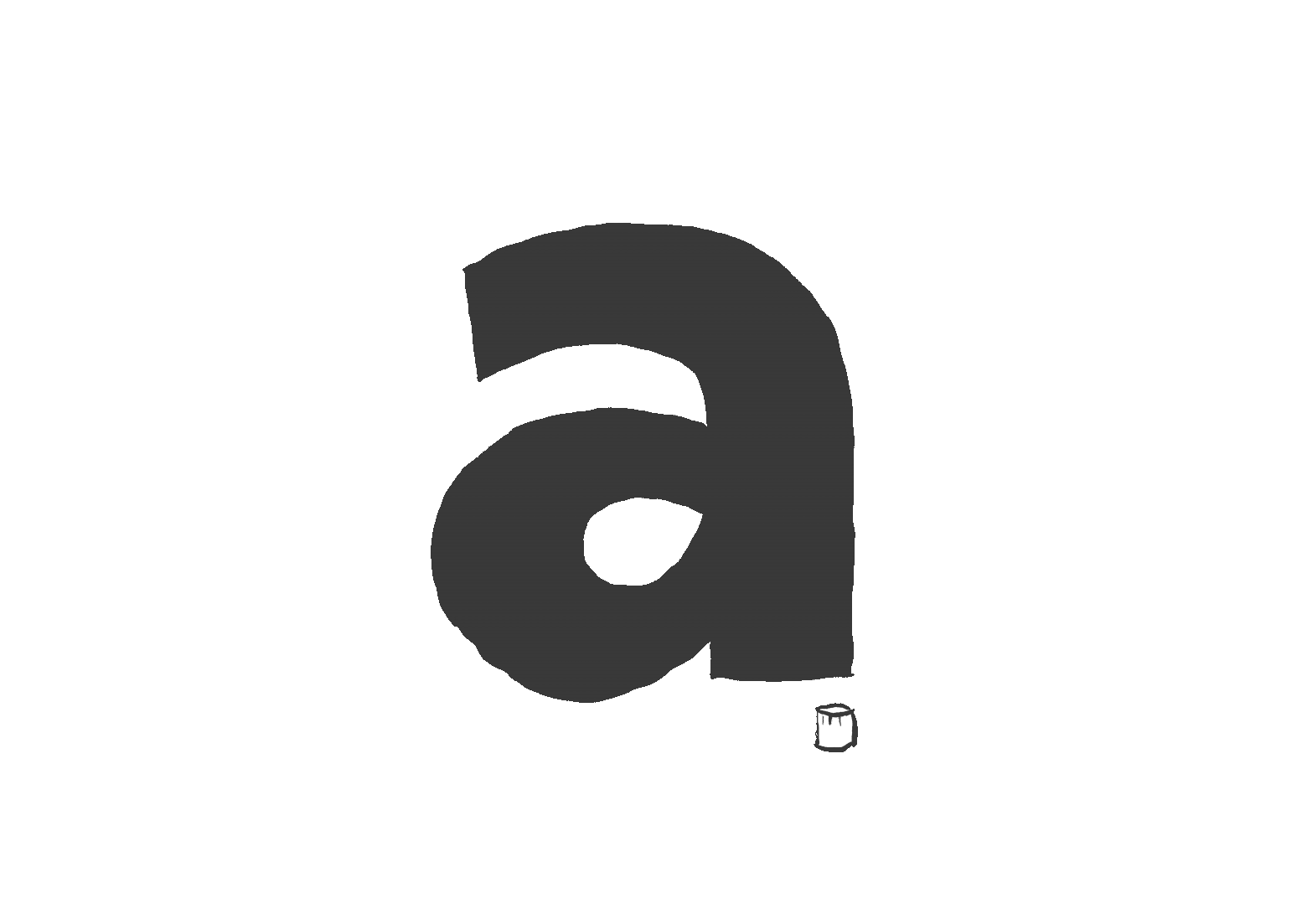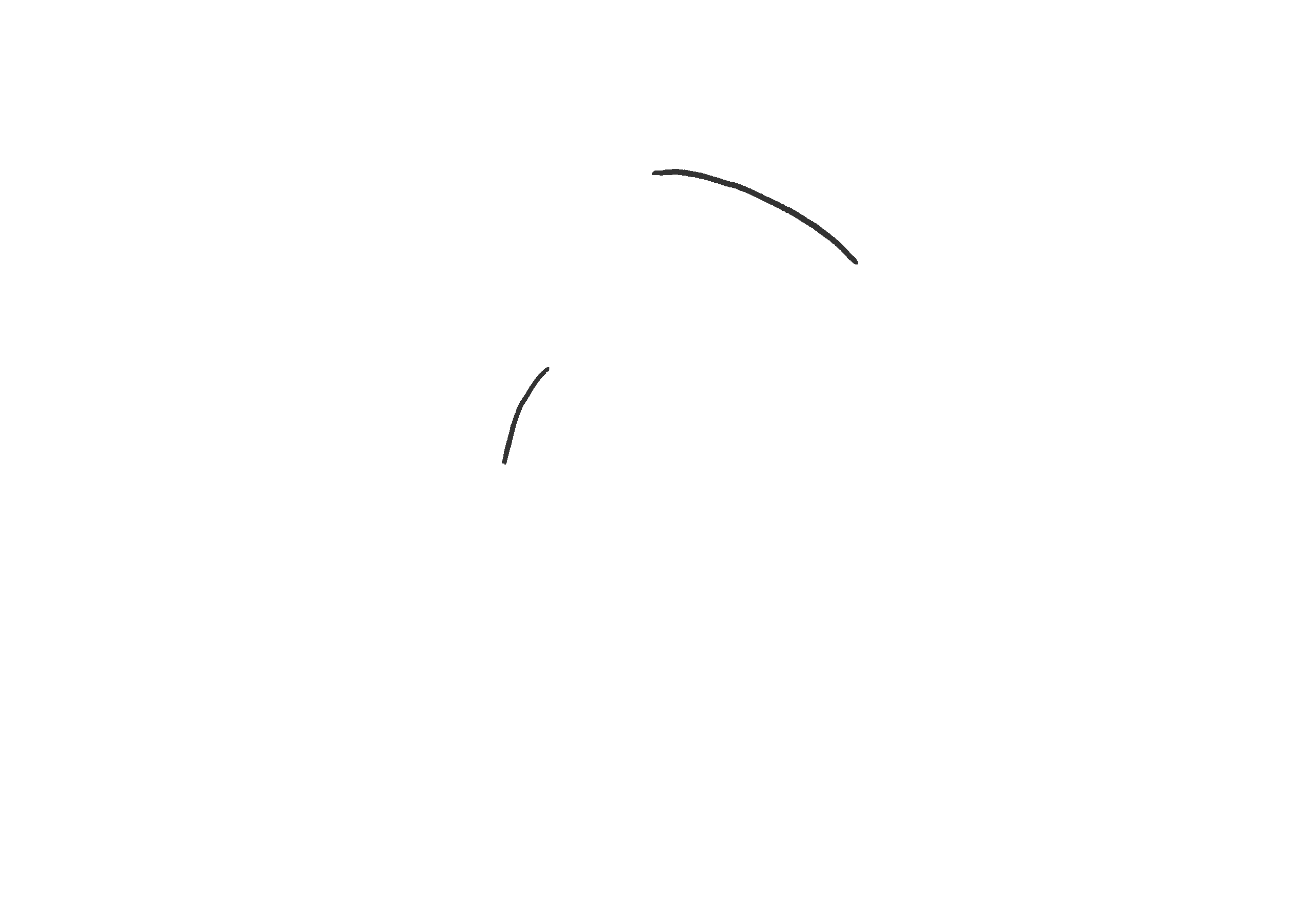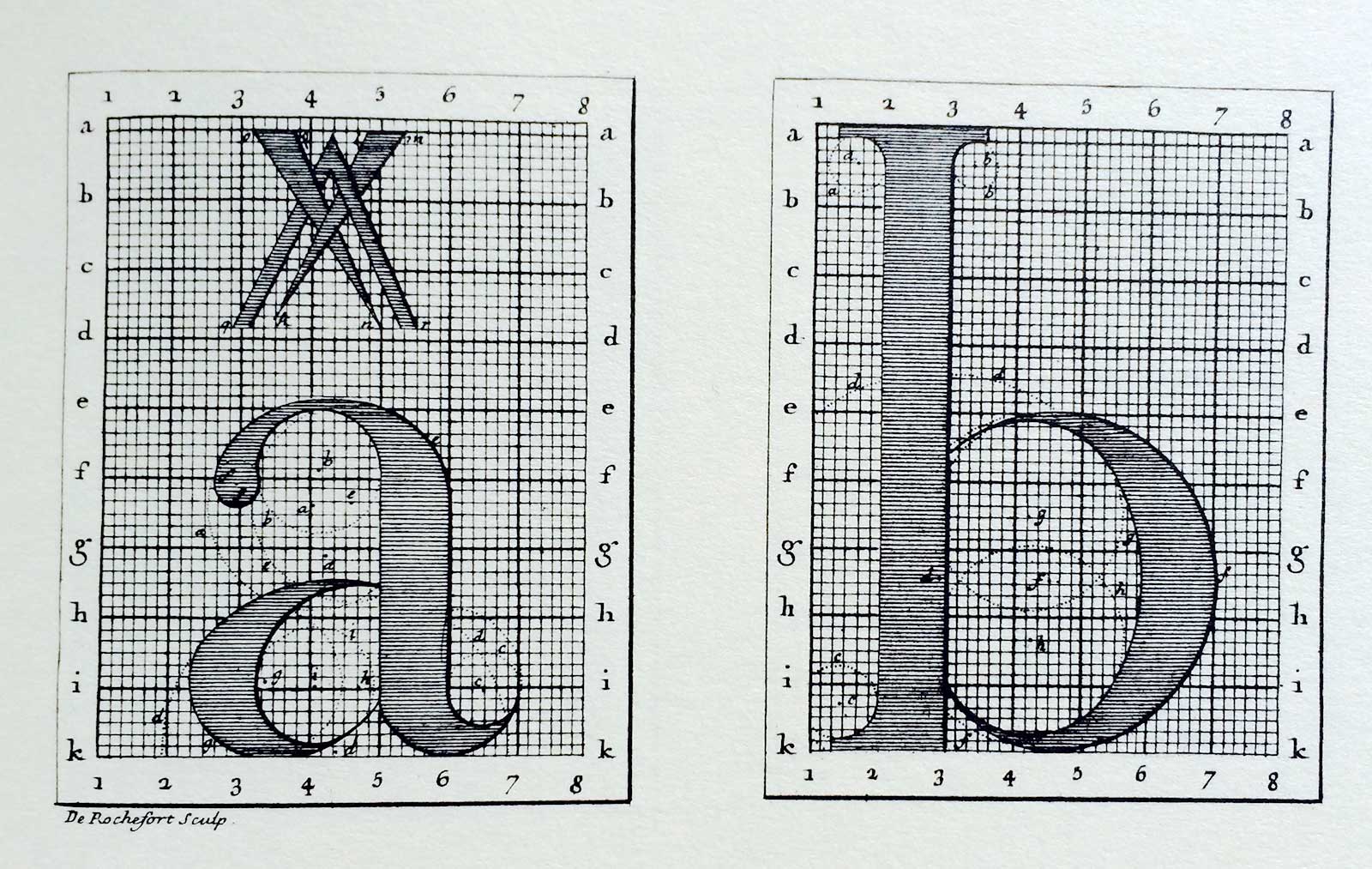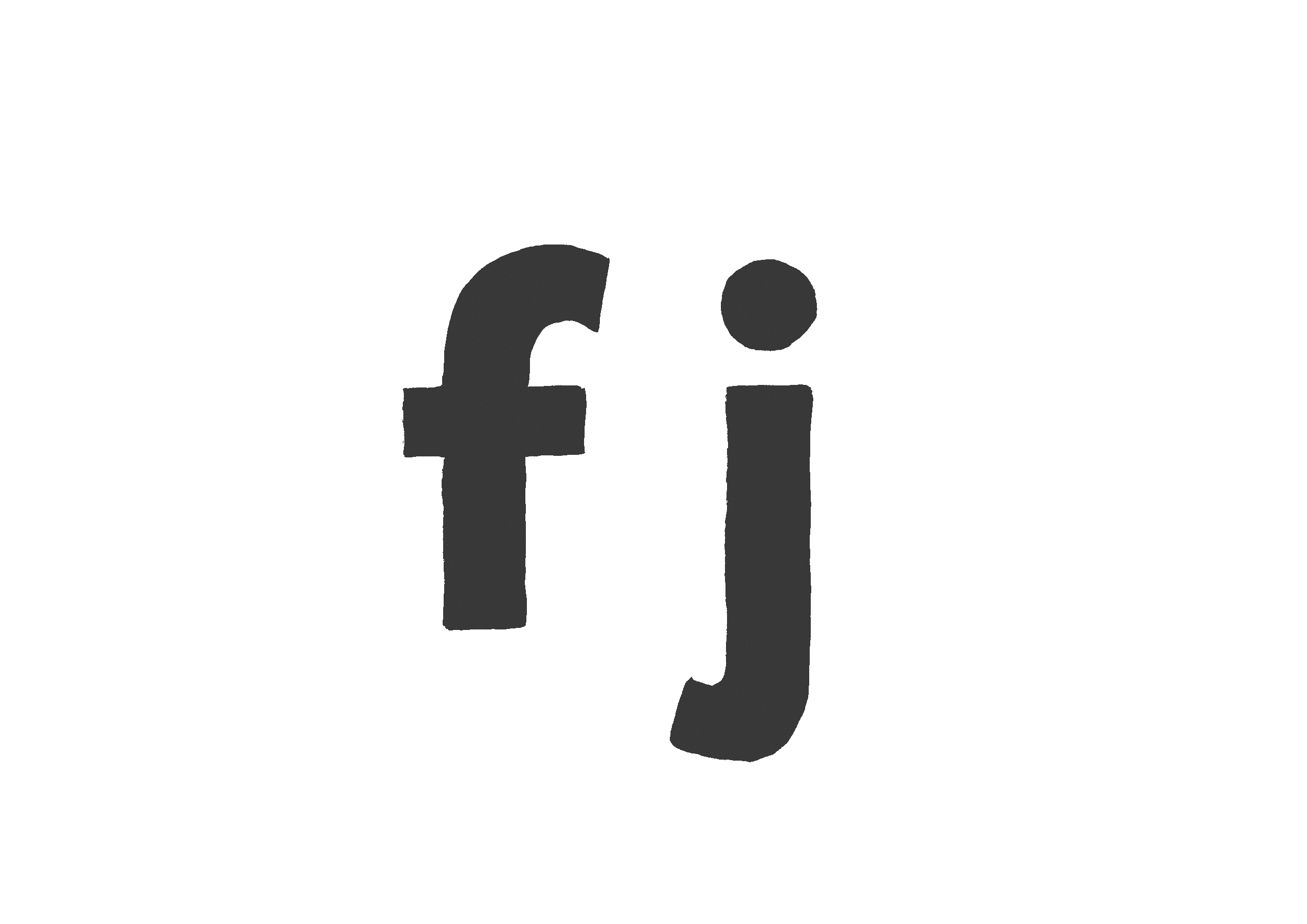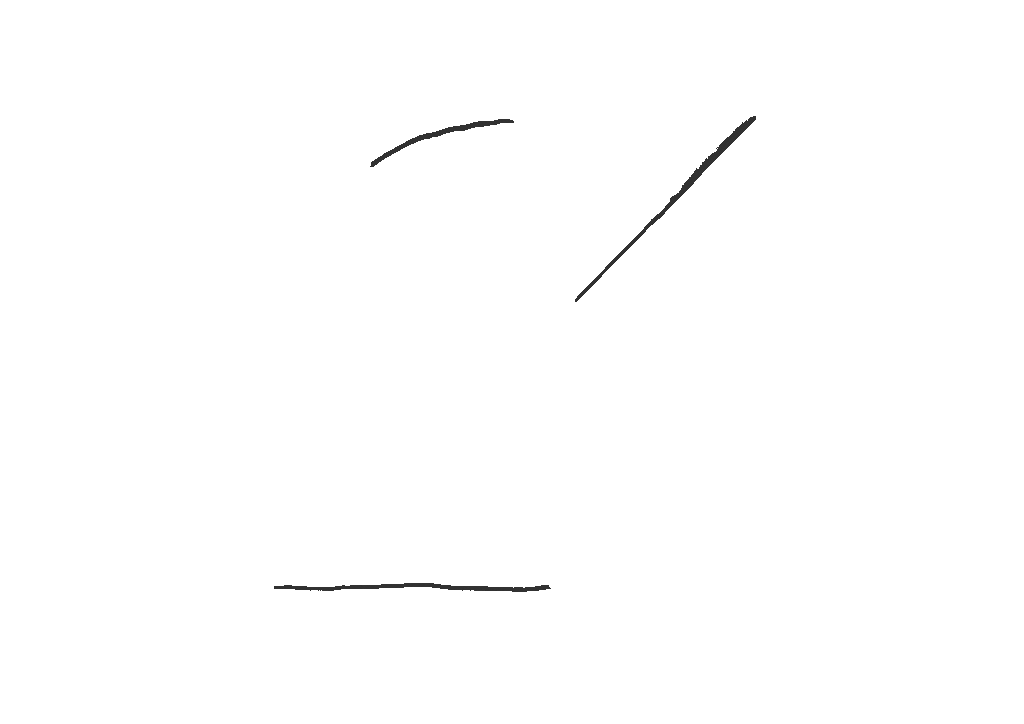
Un llamado a los diseñadores gráficos: ¡no mantengan la tipografía en una jaula!
Todos lo hemos hecho. Abres tu herramienta de edición de vectores, dibujas un círculo perfecto, dibujas otro dentro del primer círculo, recortas el segundo, alineas todo el círculo con la cuadrícula en la pantalla del editor, de modo que la curva del círculo exterior coincida perfectamente con las reglas, y ahí lo tienes, tienes una letra: O. Es claro, simple y, lo más importante, es Alineación. Se siente como la esencia de la letra, por lo que es prácticamente indiscutible. ¿Correcto?
Aquí hay otro escenario: estás trabajando en una marca denominativa y has elegido tu última fuente favorita para componer el nombre de tu marca. Pero ahora te enfrentas a algunas formas de letras sutiles, ninguna de las cuales parece tener un patrón modular que pueda descomponerse y volver a ensamblarse fácilmente: las letras redondas no se basan en círculos geométricos, el espacio entre letras no es igual e incluso dentro de la misma letra, ¡el grosor de los trazos es diferente! Tu instinto es reducir estas idiosincrasias, alinear todo con la cuadrícula y, una vez más, buscar la versión más esencial y evidente de la forma en una composición configurada a un centímetro de su vida.
obsesión por el orden
En el mundo del diseño visual, muchos de nosotros nos sentimos atraídos por los conceptos de orden, simetría y control. Nos aseguran que los productos que producimos se ajustan a estándares prescritos y se ajustan a un conjunto de estándares más divino de lo que es evidente a simple vista. Quizás le sorprenda saber que el instinto de estandarizar los tipos de letra es casi tan antiguo como el tiempo. Un ejemplo particularmente sorprendente data de hace unos cuatrocientos treinta años.
Encargado por el Rey Sol Luis XIV, Roma del rey (King Roman) es un tipo de fuente que sigue las fórmulas más complejas; cada curva, ángulo y serif se somete a complejos cálculos matemáticos. Pero al mismo tiempo Roma del rey Si bien se hicieron esfuerzos para perfeccionar la escritura romana mediante la racionalización matemática, no permitió que el proceso trascendiera por completo la forma y función de las letras mismas. en otras palabras, rey romano Los componentes de las formas de las letras estaban codificados, pero sus fórmulas simplemente describían una letra existente en lugar de inventarla.
Esta es a menudo una trampa común en el diseño gráfico contemporáneo: imponer reglas y pautas estrictas a todo, incluso a expensas de la identidad de la cosa misma. Hoy en día, en los entornos digitales que diseñamos, todo se puede superponer fácilmente en una cuadrícula; las aplicaciones que utilizamos marcan en voz alta la desalineación de una esquina aquí y un vértice allá. Las asimetrías quedan expuestas y cada distancia entre objetos está marcada en incrementos uniformes.
Quizás sea esto lo que nos hace susceptibles a una sobreracionalización, pero las alianzas y reglas impuestas dejan sólo un espacio muy estrecho para la creatividad.
sacrificio de personalidad
Cuando ponemos demasiado énfasis en el cumplimiento, los tipos de letra sufren. No sólo se sacrifica su personalidad sino también su funcionalidad. En los últimos años, muchas marcas denominativas y aplicaciones tipográficas famosas se han convertido en poco más que abstracciones, simplificadas hasta el punto de perder cualquier identidad. En otros casos, las formas de las letras fueron tan completamente subvertidas que se perdió su atractivo estético, y sus trazos se retorcieron y recortaron para ajustarse a las reglas de composición.
Sin mencionar la pérdida de legibilidad: cuanto más se modularizan las formas de las letras, más formas comparten con sus vecinas y más oscuras e intercambiables se vuelven.
Irónicamente, cuanto más intentamos utilizar reglas matemáticas para reducir las letras a su esencia, más nos alejamos de su verdadera naturaleza. En el sistema de escritura latina, muchas letras se componen de unos pocos trazos simples y se forman alrededor de una estructura básica circular o rectangular. Pero, para empezar, es casi seguro que no eran perfectos. Durante la mayor parte de la historia de la escritura, se escribieron con pincel, inscripción o letra. Heredan los matices de las herramientas que utilizan, matices influenciados por la velocidad a la que pueden hacer marcas en superficies específicas y las imperfectas habilidades humanas que las crean. Si tuvieran tendencias geométricas, habrían surgido de ellas a lo largo de siglos de evolución.
Lecciones de Mondrian
En el panorama visual más amplio, hay muchas similitudes: la aparente perfección geométrica contradice los matices y las peculiaridades humanas. Aunque limitó su abstracción a líneas rectas y colores primarios, Piet Mondrian no colocó formas geométricas perfectas en el lienzo. Sus pinturas muestran una lucha por el ideal absoluto y, por lo tanto, se caracterizan por la textura de las pinceladas, líneas que no son exactamente paralelas y áreas de diferente translucidez de la pintura.
De hecho, si recrearas una de las obras neoplasticistas de Mondrian en el ámbito digital, podrías lograr sus ideales, pero también perderías la calidez y la tensión de su trabajo y terminarías con algo insulso y obvio.
Entonces la letra O no es un círculo perfecto. Sí, es redondo, pero es más alto que ancho. También es superior a H e inferior al valor inicial. En sus polos, el grosor de los trazos es más claro que en el ecuador. Eso es lo que la convierte en una letra, a diferencia de la forma. La letra S es completamente asimétrica, sobre todo si resistimos la tentación de instalar un círculo perfecto en su mostrador, como la tentación de ver el logo del DVD perfectamente colocado en la esquina de la pantalla.
Las letras f y j no son gemelas Jekyll y Hyde, una es amable y recta, la otra está al revés y siniestra. En cambio, la f tiene una curvatura más generosa y hombros lo suficientemente anchos como para cubrir el ancho necesario de su travesaño. En comparación, j es más compacto y puede que ni siquiera sea tan alto. Son hermosos, concretos y familiares, incluso sin la retícula subyacente que nos asegure lo que son.
más allá de la red
Así aparecen las letras cuando decidimos mirarlas tal como son. Son matizados, expresivos, complejos y simples al mismo tiempo. Se agrupan para formar sílabas, palabras y frases. Llevan personalidad, significado e historias. Fueron creados por nosotros, no enviados por civilizaciones alienígenas avanzadas.
Las mejores fuentes permiten que las formas de las letras se mantengan fieles a su forma mientras les dan forma con el mismo estilo. Los mejores tipos de letra y logotipos están diseñados para abarcar y resaltar las formas de las letras, aprovechando su poder inherente.